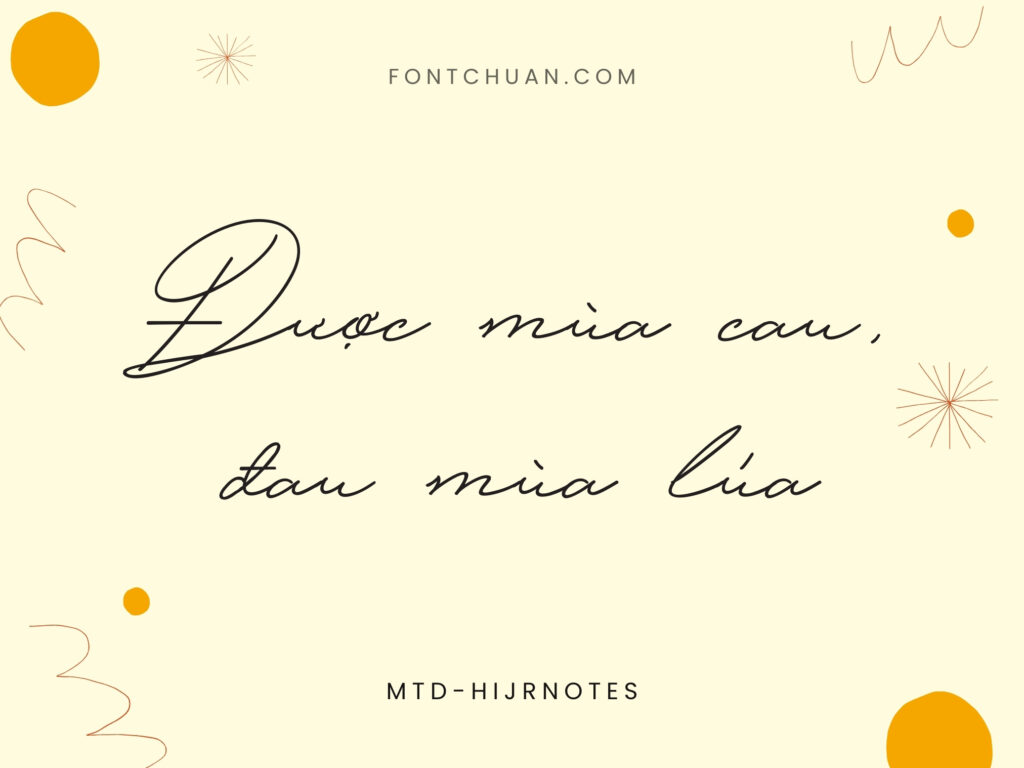
Font MTD Hijrnotes Việt Hóa
Tác giả Font: Mikrojihad Typography
Font MTD Hijrnotes là một phông chữ viết tay mang phong cách thư pháp hiện đại, được thiết kế bởi Mans Greback và Việt hóa bởi Mộc Hạ. Font này hỗ trợ đầy đủ tiếng Việt cùng hơn 90 ngôn ngữ khác, mở rộng khả năng ứng dụng trong các thiết kế đa ngôn ngữ. Đây là một trong những phông chữ được cộng đồng thiết kế đánh giá cao và sử dụng trong nhiều dự án sáng tạo, đáp ứng nhu cầu đa dạng của người dùng.
MTD Hijrnotes nổi bật với các đường nét mềm mại và uyển chuyển, mang đến cảm giác thanh lịch và sang trọng. Font rất phù hợp cho các thiết kế logo, tiêu đề, bao bì sản phẩm, thiệp mời và các ấn phẩm đòi hỏi sự tinh tế và nghệ thuật. Các ngành nghề phù hợp bao gồm quảng cáo, giáo dục, công nghệ, thiệp cưới và ảnh cưới. Font này cũng lý tưởng cho các sự kiện như Tết, Giáng sinh, Valentine và các lễ hội khác.